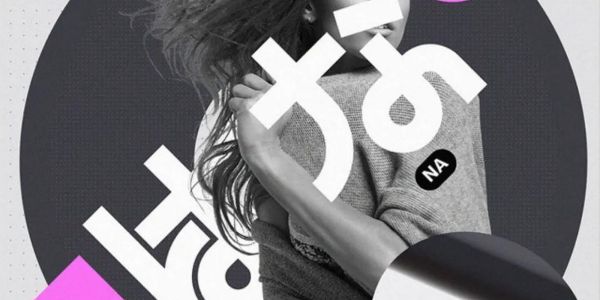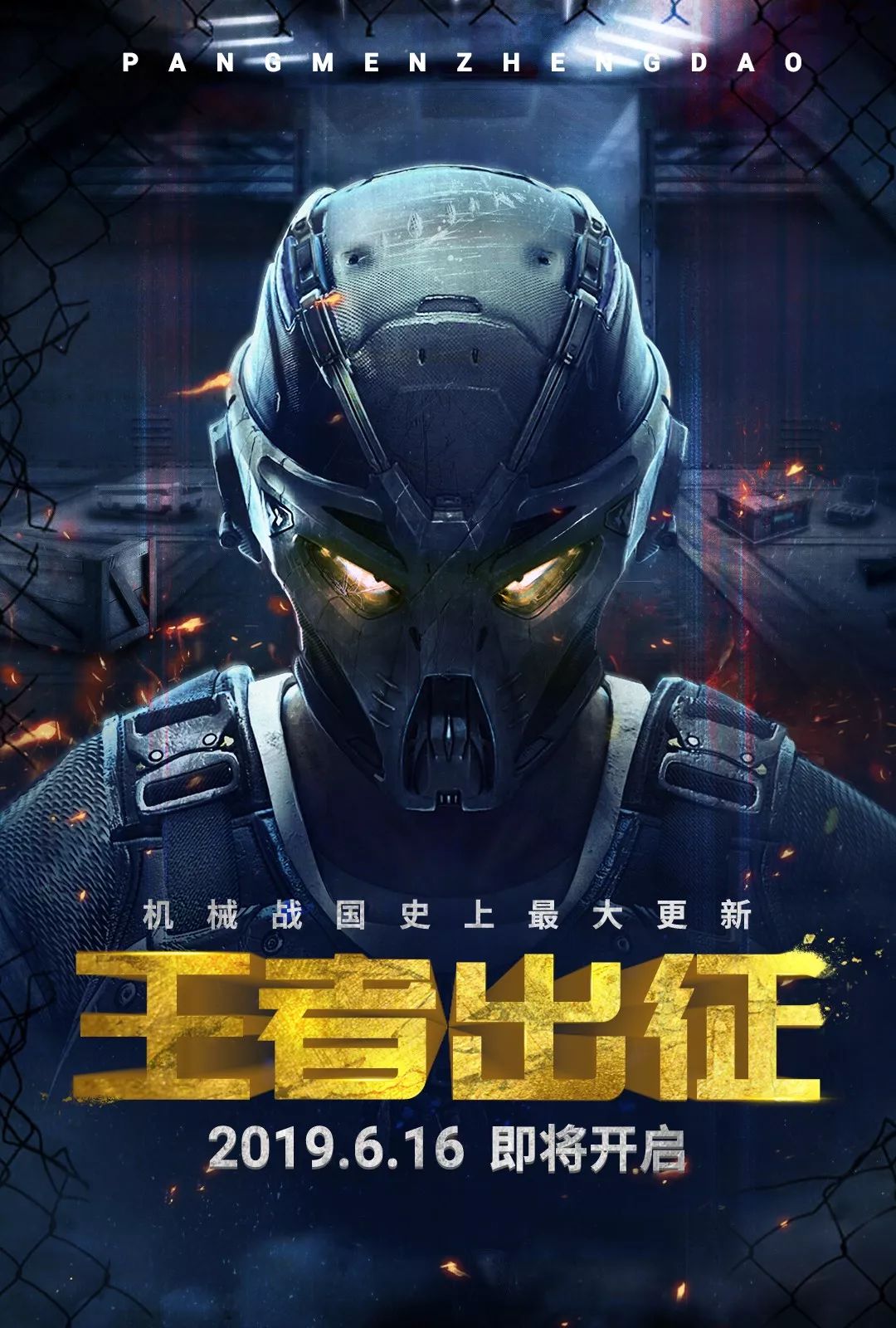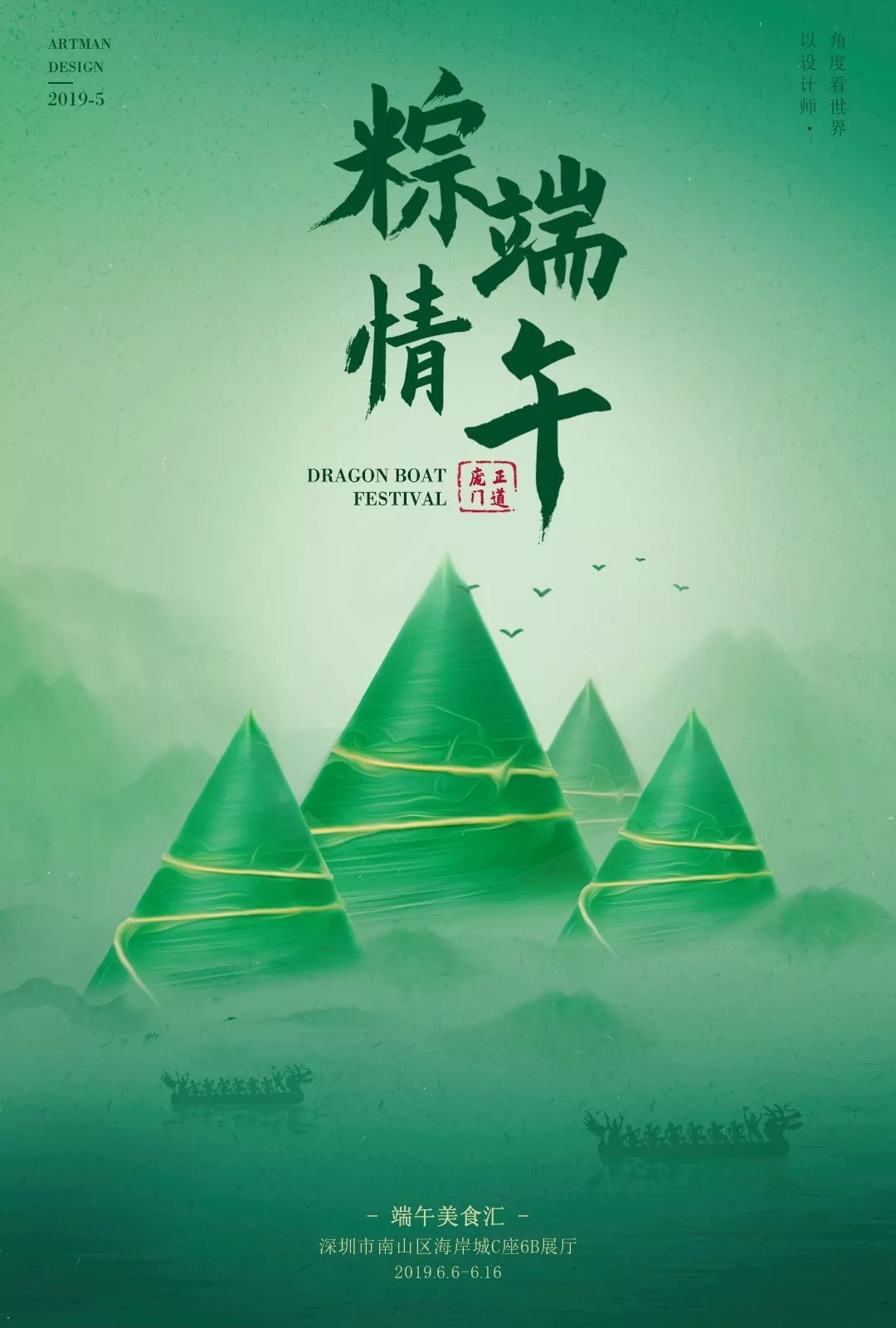
立体字很难吗?三招教你制作立体字设计
今天教你用字体做一些延申和实际应用吧!!
立体字-方法1
首先把字复制一份备用,居中于整个画布,栅格化变成普通图层。选中图层文字执行滤镜菜单下扭曲-极坐标,弹出框里选择第二个选项 极坐标到平面坐标后确定。在选择图像菜单下的图像旋转-顺时针90度。
继续滤镜菜单下的风格化-风,在弹出里选择,方法:风、方向:从左,确定。接着按快捷键CTRL+ALT+F,多按几次。在到图像菜单下选择图像旋转-逆时针90度。
又滤镜菜单下找到扭曲-极坐标,这次选择平面坐标到极坐标。立体效果完成了。接着把之前复制的字放在立体字上调整颜色立体效果更明显啦。
立体字-方法2
选中文字层按右键在弹出下拉菜单里选中从所选图层新建3D模型,这时画面出现3D视图。在回到图层面板选中背景图层单击右键在弹出中选择明信片。选中文字和背景图层,在菜单栏3D下拉选中合并3D图层。
回到3D属性面板,选中画布面板下角的小球调整方向,双击3D属性面板里的文字层双击,在弹出里调整凸出深度改文字的厚度数值稍微调小一点。
在回到3D属性面板选中文字和背景图层然后执行左对齐。还是选中两个图层情况下点击画布下面的小球,鼠标稍微向下单击右键,在弹出框里选择默认视图。字体方向调整好了。
在双击3D属性面板里的文字层,在弹出里把文本颜色改成白色。接下来在3D菜单栏里找到渲染3D图层,稍微等一会3D立体效果就完成了。
立体字-方法3
最最简单变立体字
打好字,把文字变成图层
复制一层稍微缩小移动一下位置。
接着按alt+ctrl+shift+t会复制出一层
不要停继续重复,直到立体效果满意为止。
自制书法字
当书法字体不是每一笔话都是自己想要的样子,怎么办?
找到毛笔笔画的素材,在打好字上修改笔画
可以拥有属于你的书法字你
虽然大师的神功学不来
却可以活用今天的自制书法字体
用不同字骨架拼属于你的书法字